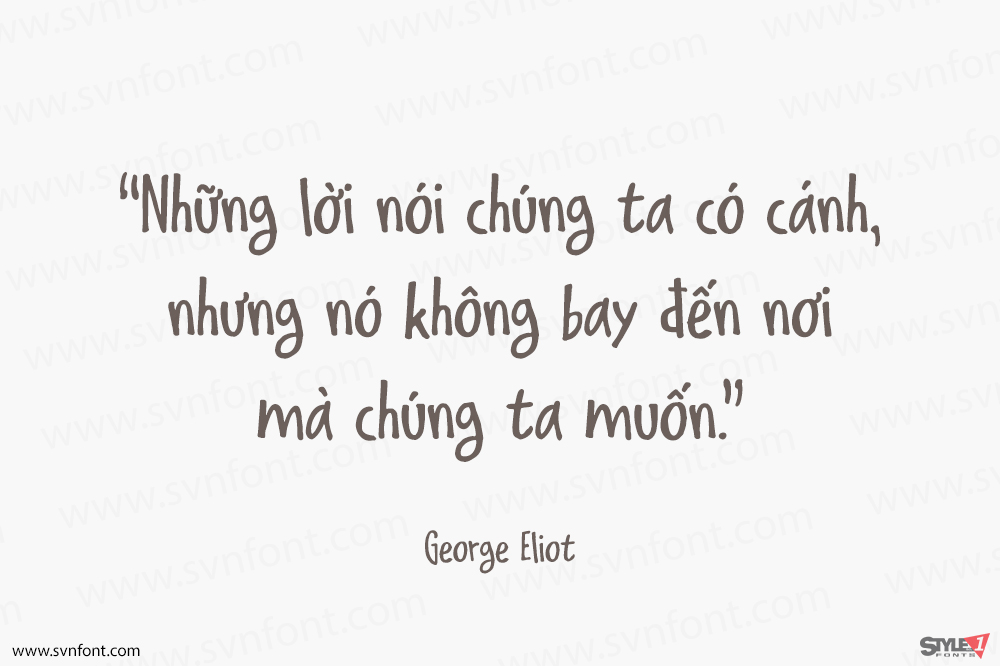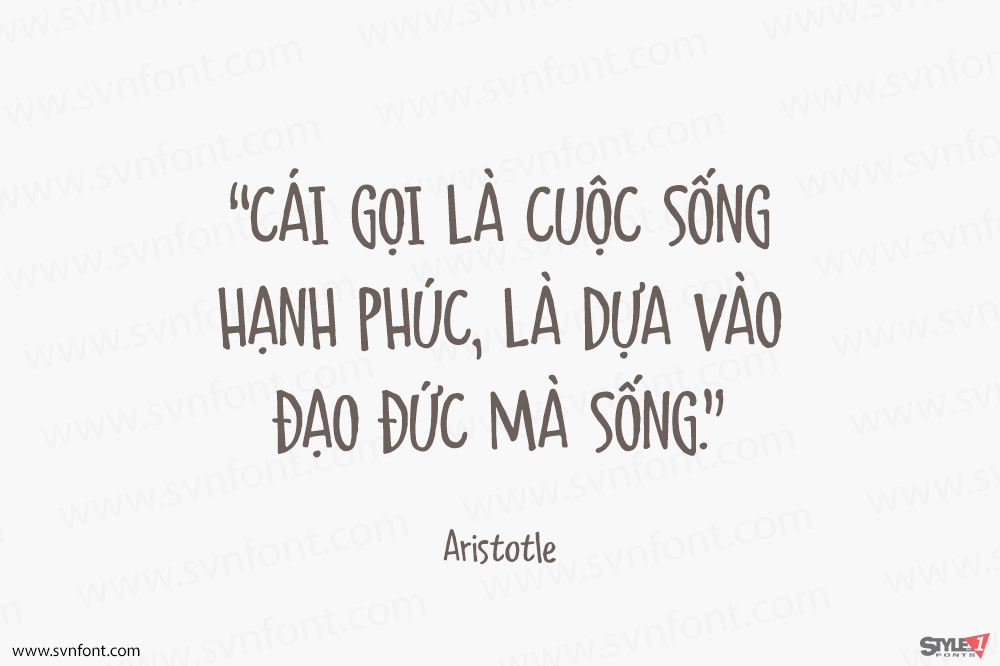
Tôi thích những font trông như các ghi chú viết nguệch ngoạc… nên tôi đã tự tạo ra một font! Delivery Note được vẽ bằng bút Sharpie trên giấy. Tôi không “làm sạch” các glyph quá nhiều, vì muốn giữ cảm giác như một nét chữ ghi chú thật sự. Font đi kèm các ligature chữ thường kép và một bộ doodle vui nhộn.
Nhà thiết kế: David Kerkhoff